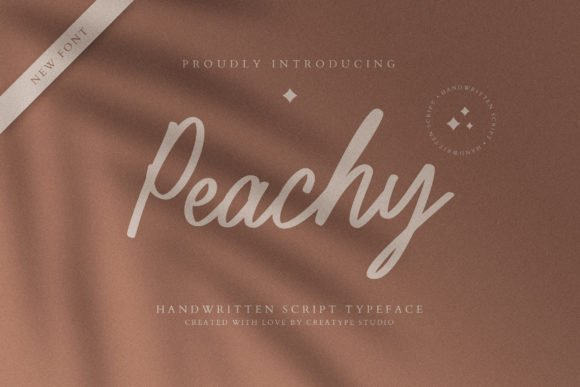
[Creativefabrica] Peachy Font (2021)
Название: Peachy Font (2021)
Peachy Script - это красивый и изысканный шрифт.
Он имеет стильный, элегантный и современный вид, который можно использовать для логотипов, брендинга, приглашений, канцелярских принадлежностей, свадебных дизайнов, постов в социальных сетях и многого другого!